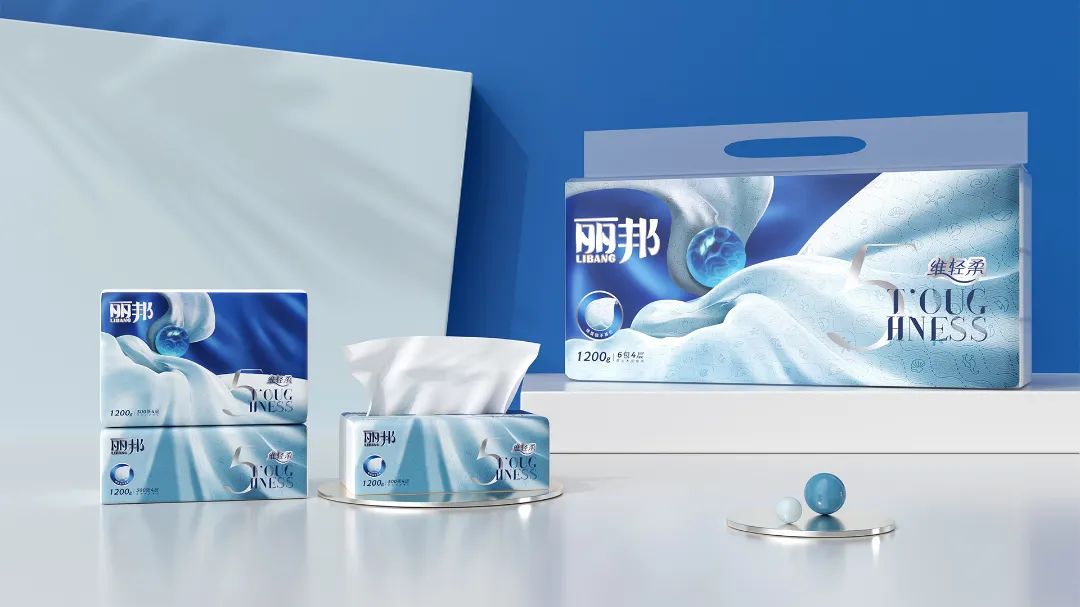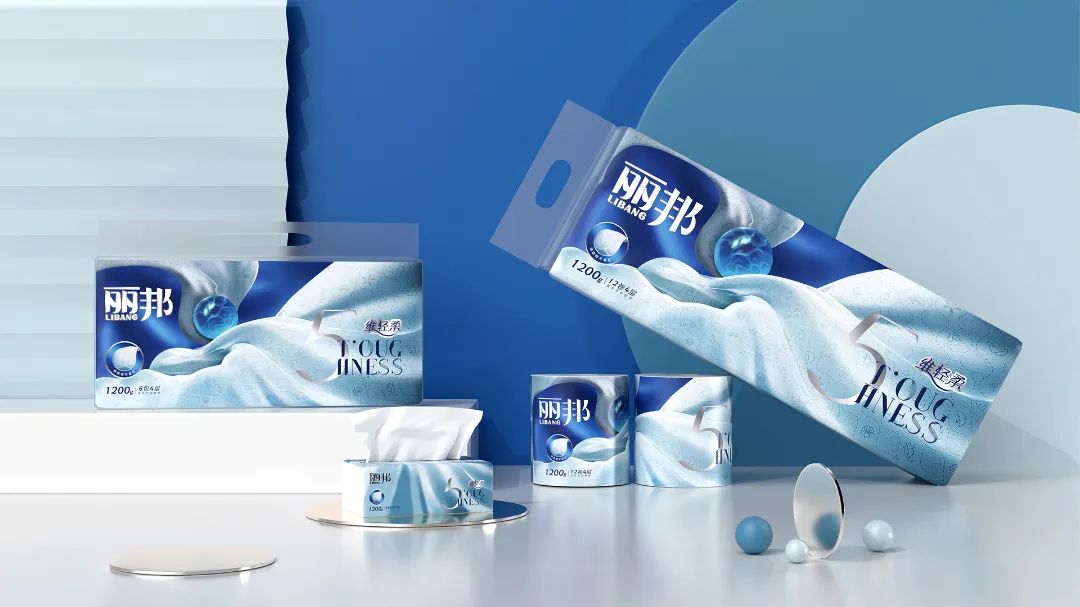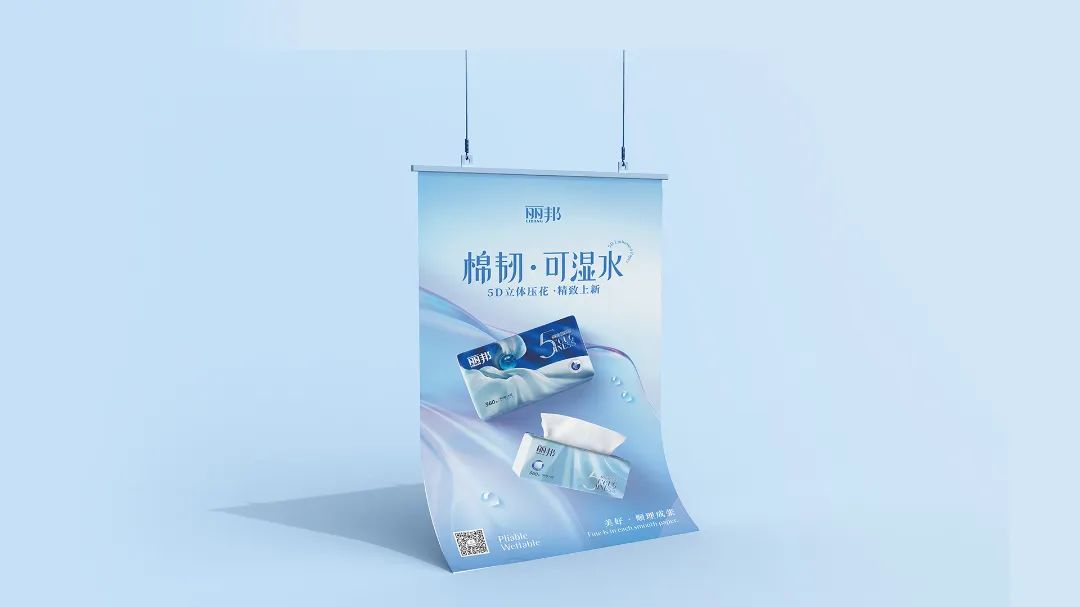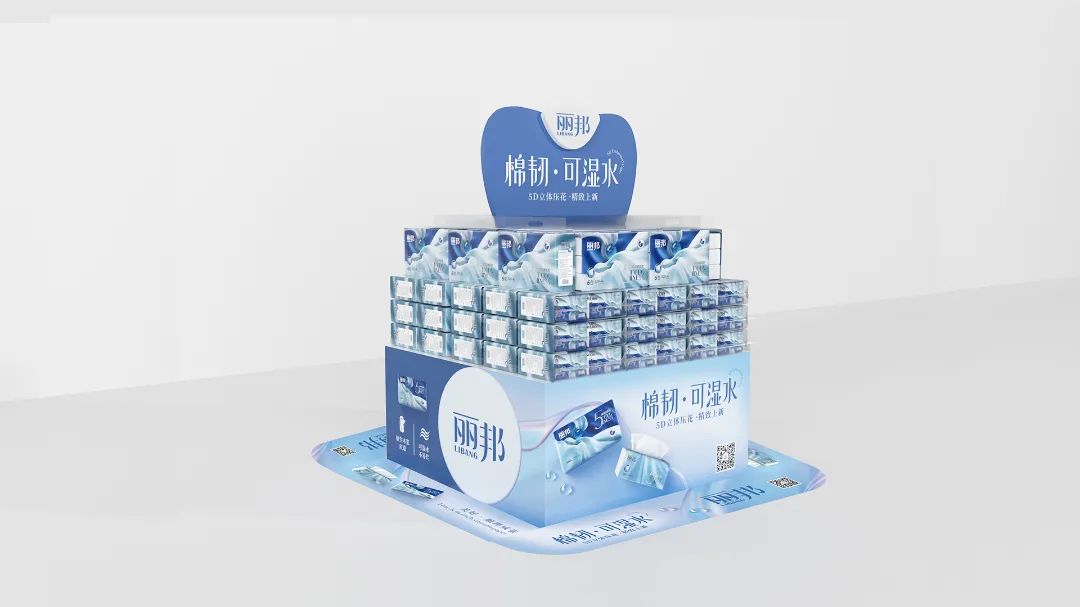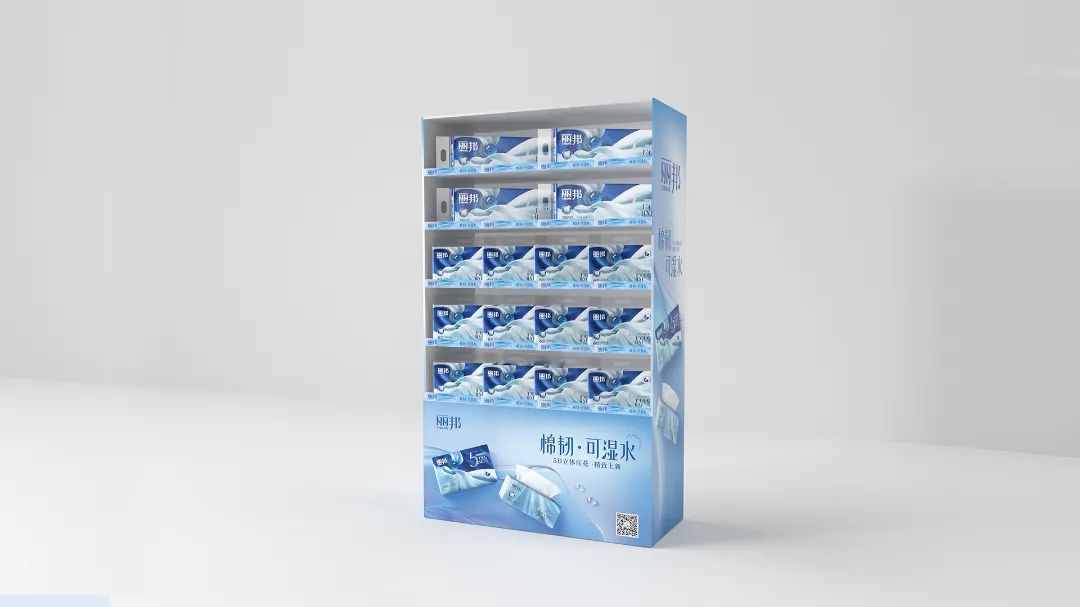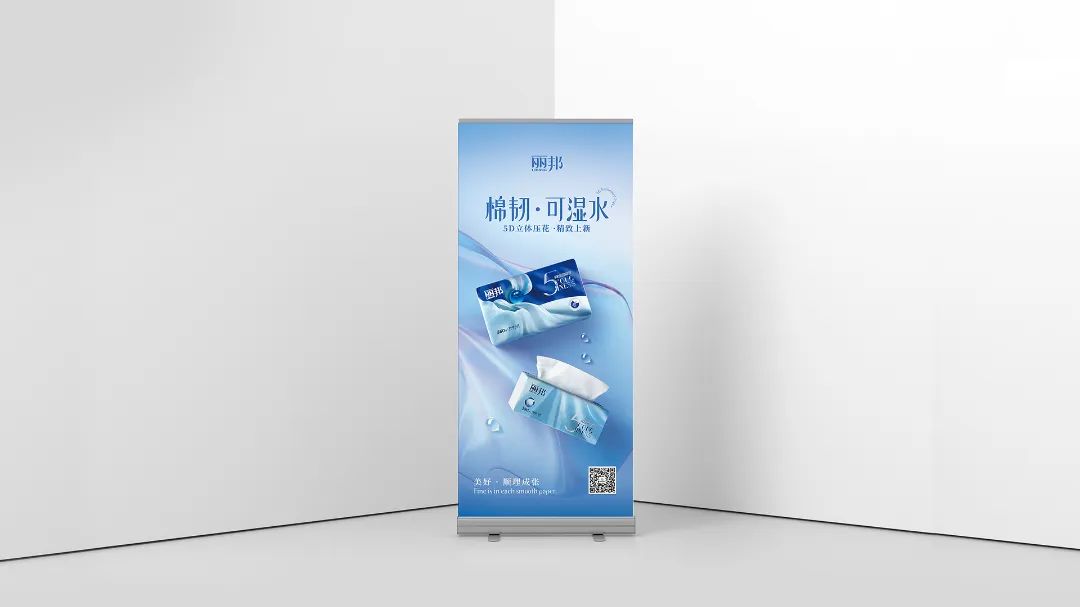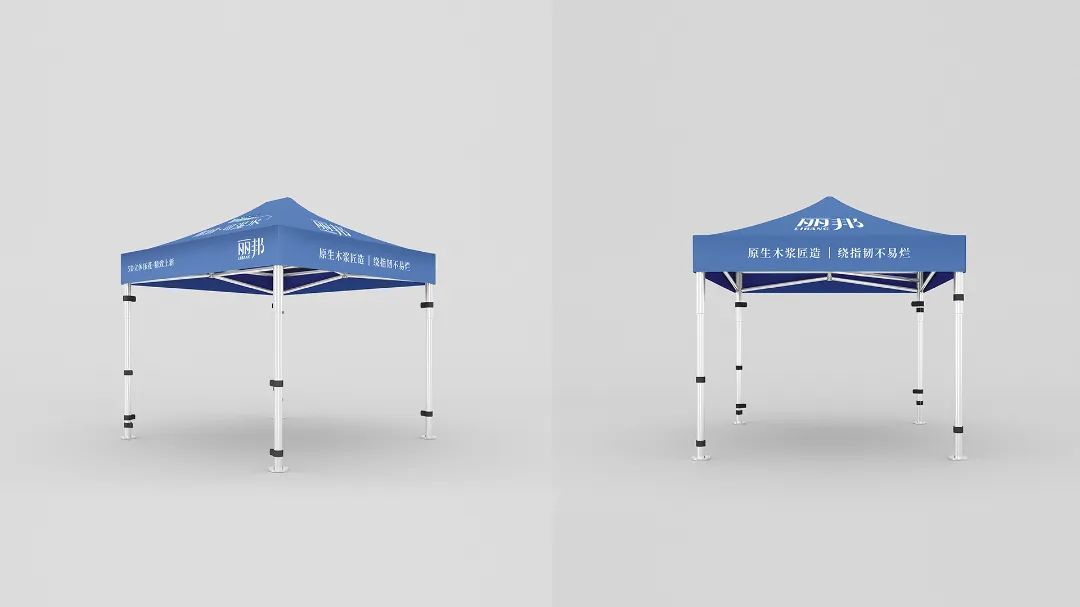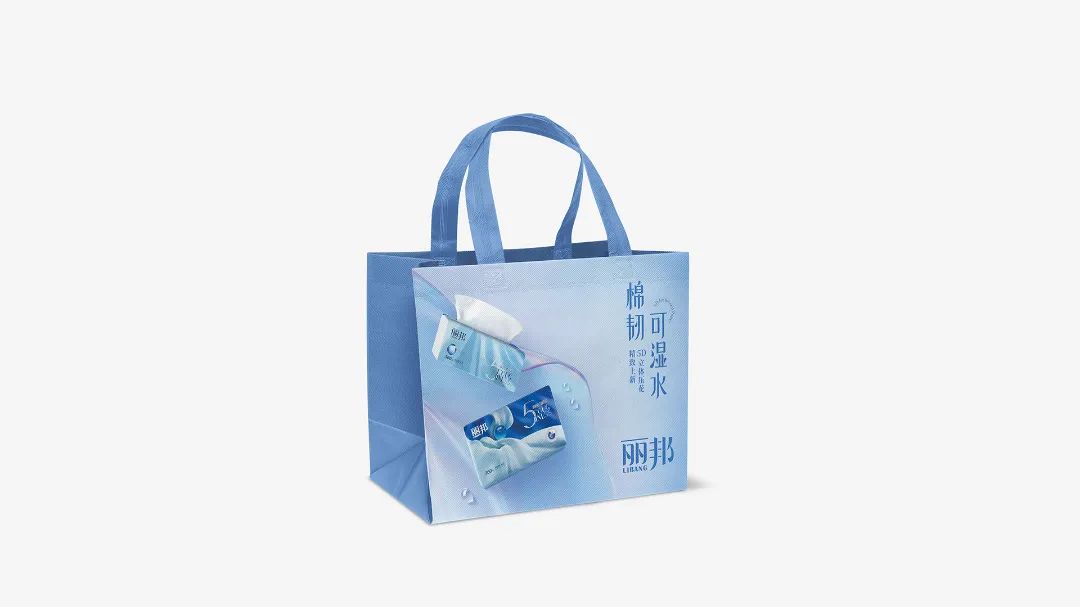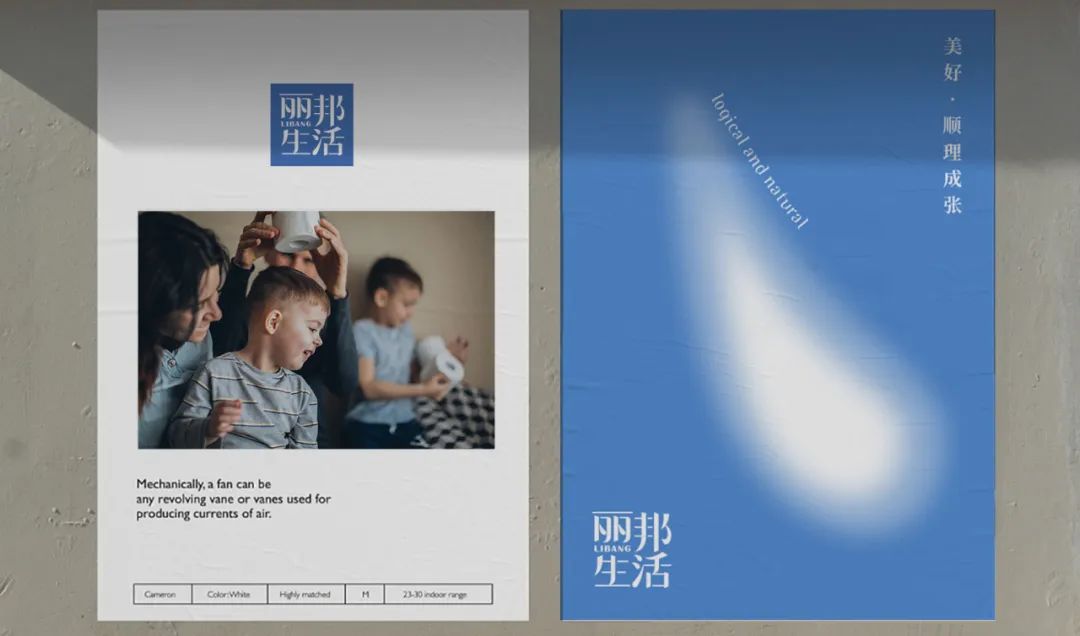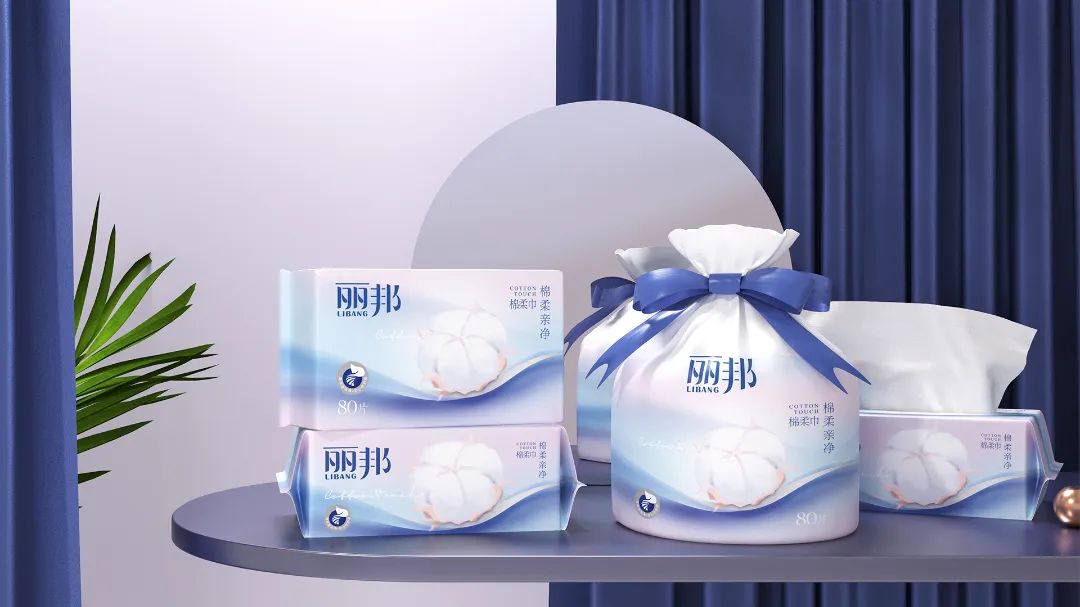
【品牌全案服務(wù)】麗邦×在水一方 | 以終為始的華麗轉身
前言
麗邦集團始創(chuàng )于1991年,長(cháng)期專(zhuān)注衛生護理用品與服務(wù)領(lǐng)域,竭力為每個(gè)家庭和用戶(hù)提供高品質(zhì)高價(jià)值的生活用紙全系產(chǎn)品及服務(wù)。
麗邦品牌榮獲國家工商總局認定“中國馳名商標”。麗邦集團產(chǎn)品覆蓋全國市場(chǎng)近5000個(gè)銷(xiāo)售終端,市場(chǎng)地位穩居全國紙業(yè)9強行列。
以終為始,探索發(fā)展
秉持“服務(wù)至上,實(shí)干興邦”核心思想,麗邦致力于成為中國紙品衛品領(lǐng)域實(shí)干型企業(yè),從生產(chǎn)型企業(yè)進(jìn)階為銷(xiāo)售服務(wù)型企業(yè)。
麗邦實(shí)施制度人性化,流程科學(xué)化,標準嚴苛化的發(fā)展理念,以終為始,進(jìn)階探索發(fā)展之道——立而筑基,力以?xún)葻?,礪己升級,麗致實(shí)現,塑造優(yōu)質(zhì)企業(yè)的全新形象。
汲取麗邦企業(yè)核心特質(zhì),LOGO視覺(jué)煥新升級。主圖形通過(guò)不同形態(tài)的葉子元素組合,演化出LB創(chuàng )意。
純綠表現麗邦企業(yè)永葆生命力的發(fā)展態(tài)勢,代表企業(yè)在組織、管理和作業(yè)形式上的立體化布局及運營(yíng)。
中英文主體以深灰色為呈現,展現企業(yè)大氣穩重的氣質(zhì),并引領(lǐng)行業(yè)邁向嶄新和健康的發(fā)展之路。
品牌重塑·長(cháng)驅直入
麗邦品牌原市場(chǎng)布局集中于華北、東北、西北等區域三、四線(xiàn)城市,即使品牌重塑升級仍要重視戰略大后方的建設,下沉市場(chǎng)于麗邦之意義不言而喻。
中國實(shí)際國情、商業(yè)業(yè)態(tài)變遷、小鎮青年崛起等因素奠定了下沉市場(chǎng)的潛力地位,麗邦關(guān)注新興90后00后人群之余,深入滲透還原真實(shí)的下沉消費主體,60后70后80后等不同代際人群的需求同樣不可忽視。
以服務(wù)思維滲透品牌,注重真實(shí)體驗,探究更好用的紙巾。從多個(gè)維度構建目標產(chǎn)品模型,追求更佳柔韌比、更高安全值、更優(yōu)性?xún)r(jià)比、更佳美觀(guān)度。
“美好生活,順理成張”
立足于“實(shí)用美學(xué)生活派”品牌角色,麗邦兩大核心價(jià)值呼之欲出,理性?xún)r(jià)值與感性?xún)r(jià)值并駕齊驅。終至理性?xún)r(jià)值關(guān)注的是使用體驗,底層邏輯為“好物·盡其用”,即所有產(chǎn)品將充分發(fā)揮其實(shí)用性,從選材、工藝、技術(shù)層面理性解決。
感性?xún)r(jià)值關(guān)注的是精神體驗,底層邏輯為“生活·盡其美”,即重視產(chǎn)品所帶來(lái)的附加屬性,聚焦顏值、氛圍、情緒等感性要素,達成和諧之美。
多場(chǎng)景式覆蓋,演繹實(shí)用美學(xué)生活派角色,通過(guò)系統性產(chǎn)品規劃逐步滲透到人們日常生活各場(chǎng)景中,包括且不限于戶(hù)外旅行、居家生活、青春校園、商務(wù)辦公、時(shí)尚聚會(huì )、母嬰專(zhuān)戶(hù)等。
讓紙品更有品,讓生活更生動(dòng)。
簡(jiǎn)化視覺(jué),大牌自信。新“麗邦”品牌深諳“實(shí)用美學(xué)”之道,去除不必要設計,突出品牌核心視覺(jué),干練實(shí)用,降低認知溝通成本。
賣(mài)點(diǎn)可視化,設計差異化,重點(diǎn)輸出核心訴求信息,乳霜紙巾界的自信代表,陳列效果顯著(zhù)搶眼。迎合當前消費時(shí)尚趨勢,注重產(chǎn)品顏值,擁有獨立美學(xué)思考。
IP精靈組合系列手帕紙,迎合時(shí)下年輕消費群體審美趣味,增加包裝故事性和視覺(jué)聯(lián)動(dòng)性,賦予產(chǎn)品良好的消費體驗感。個(gè)性化營(yíng)銷(xiāo),激活產(chǎn)品主觀(guān)能動(dòng)性。
終端策應·劍指市場(chǎng)
棉韌·可濕水系列攜5D立體壓花精致上新,海報購物袋堆頭展示架等終端物料一體配套,直指產(chǎn)品核心訴求。
終端訴求直觀(guān)化,聚焦核心賣(mài)點(diǎn),新視覺(jué)高維輸出,賦予產(chǎn)品更強的賣(mài)點(diǎn)表現力和說(shuō)服力。統一視覺(jué)特征,確保品牌形象和產(chǎn)品系列的協(xié)同效應最大化。
以延展性交換發(fā)展性,助終端賣(mài)場(chǎng)演進(jìn)品牌主場(chǎng),全面開(kāi)發(fā)終端物料的實(shí)用價(jià)值,夯實(shí)品牌的市場(chǎng)認知度。
無(wú)論是對于企業(yè)還是品牌,以終為始,捋順思路,以企業(yè)愿景和市場(chǎng)目標為戰略起點(diǎn),才能運籌帷幄,決勝千里。